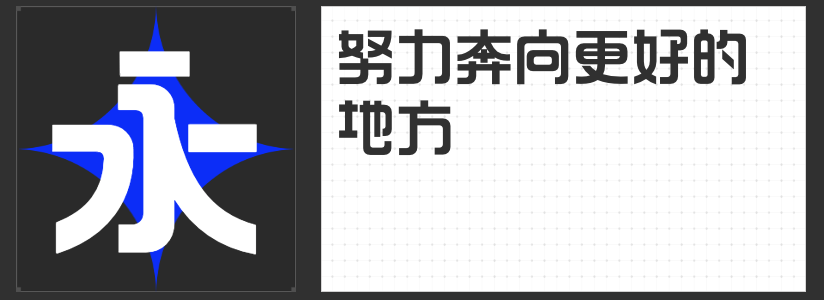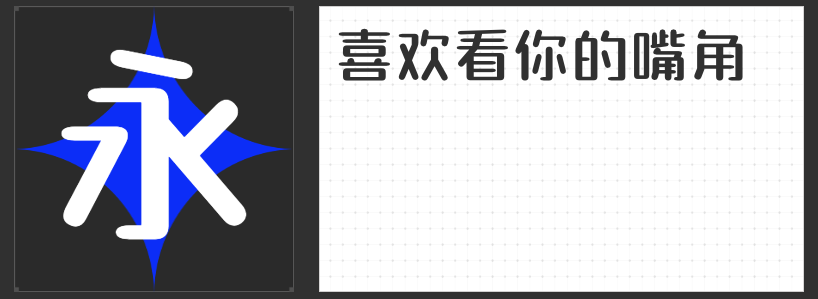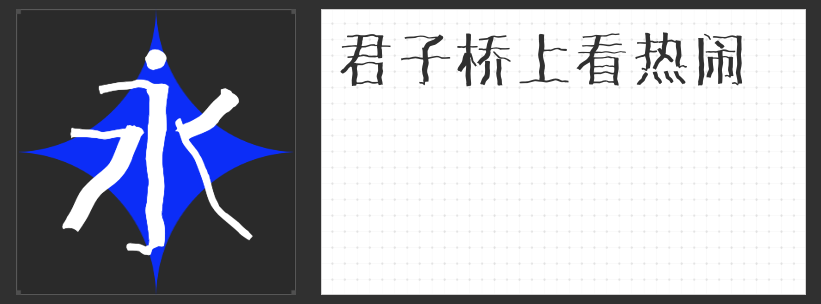
四款海报设计字体推荐:解锁视觉创意的多元表达
海报设计是视觉艺术的竞技场,字体作为信息传递与风格塑造的核心元素,往往决定着整体设计的张力与记忆点。以下四款风格迥异的字体,以独特的造型语言与审美趣味,为海报创作注入鲜活灵感。
一、励字笑语声声简
这款字体以拙朴线条勾勒童真轮廓,圆融的笔画与均匀的布白营造出无攻击性的可爱气质。圆弧转角与留白空间的巧妙运用,既保留了手写书法的温度感,又通过现代审美重构了装饰趣味。其辨识度强的特点使其在二次元与三次元语境中均能游刃有余——无论是萌系文化海报还是亲子活动宣传,都能以柔软的视觉语言唤醒观者的童心共鸣,传递温暖治愈的氛围。
二、造字侠地铁修悦体 大粗
方正造型与平直切口碰撞出工业感的几何美学,人工拼贴的不规律性则赋予字体动态的呼吸感。多变的重心与留白制造出视觉陷阱,引导观者的视线在排版中跳跃游走。
三、万人字造李峰波光体 常规
以水波纹为灵感的笔形设计,让文字仿佛在空气中荡漾开来。富于变化的曲线与轻盈的节奏感,为海报注入东方美学的写意气质。无论是奢侈品广告的优雅、饮品海报的清爽,还是节日宣传的梦幻,波光体都能以流动的视觉语言传递情绪,让标题成为画面中灵动的点睛之笔。
四、字恋狂灵怪简
古灵精怪的连笔设计与几何化折笔处理,构建出超现实的字体宇宙。流畅恣意的笔画如意识流般自由延展,既保留了书写的韵律感,又通过解构重组释放出叛逆的创意能量。
这四款字体以差异化美学满足多元设计需求,无论是追求温暖治愈、先锋冲击、浪漫流动还是叛逆创意,都能找到对应的表达工具,助你打造令人过目难忘的海报作品。